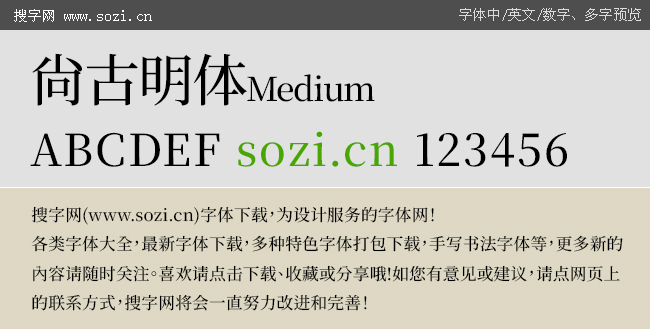
尚古明体Medium
搜字网提供一款尚古明体Medium中文字体下载,尚古字体是一套泛中日韩传承字形(旧字形),基于思源黑体、思源宋体、思源等宽以及思源系列衍生字型制作,包含黑体、明体、圆体、等宽以及简转繁字型。这款字体无论是个人还是企业都可以自由免费商用,无需知会或者标明原作者。适合包装设计、海报设计、广告设计等应用。
• 风格类别: 宋体